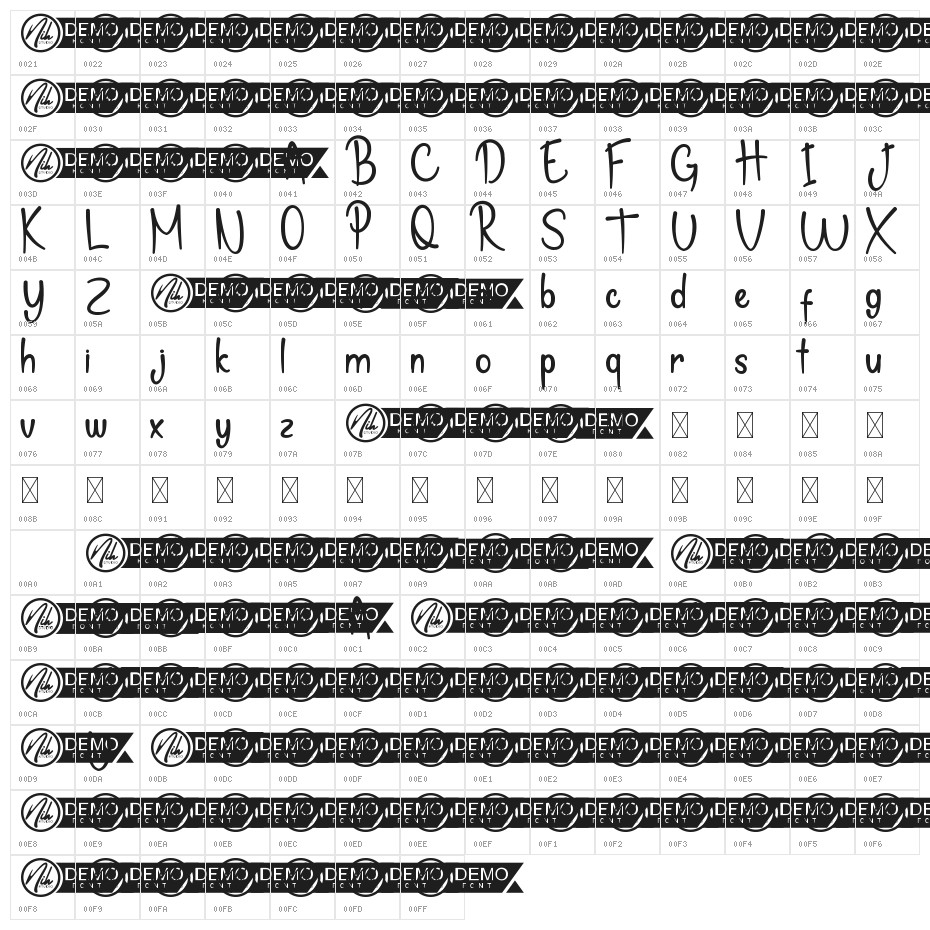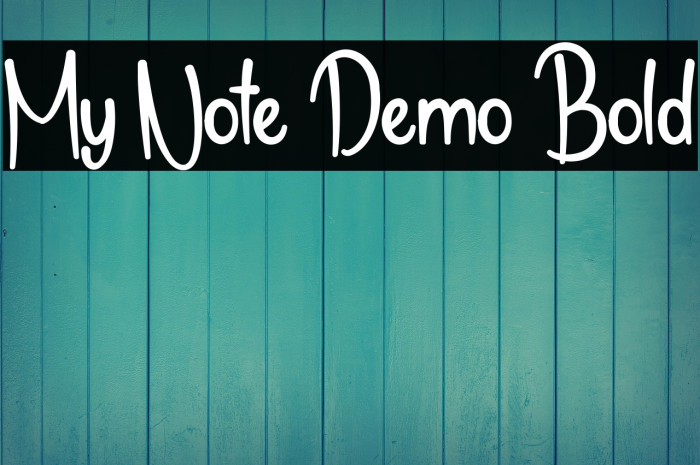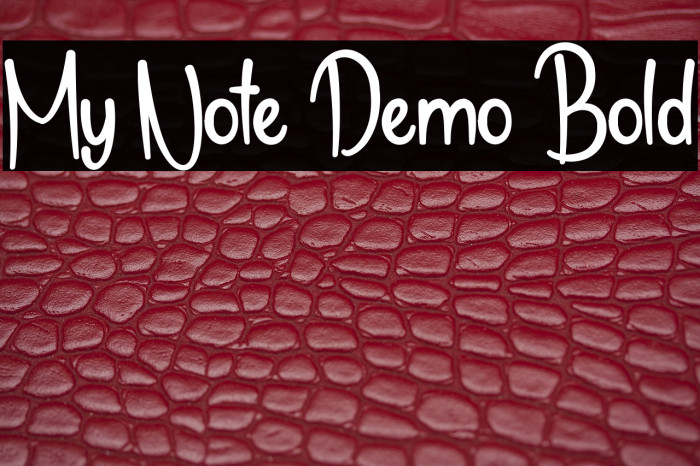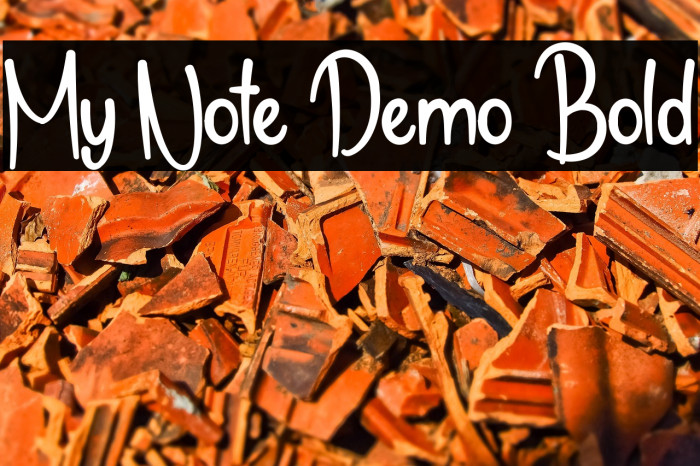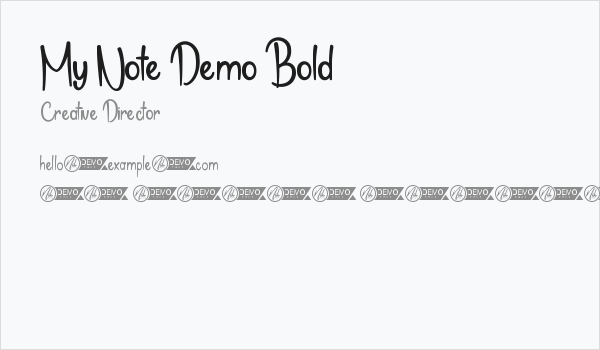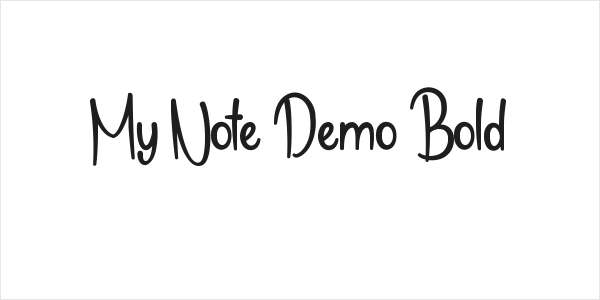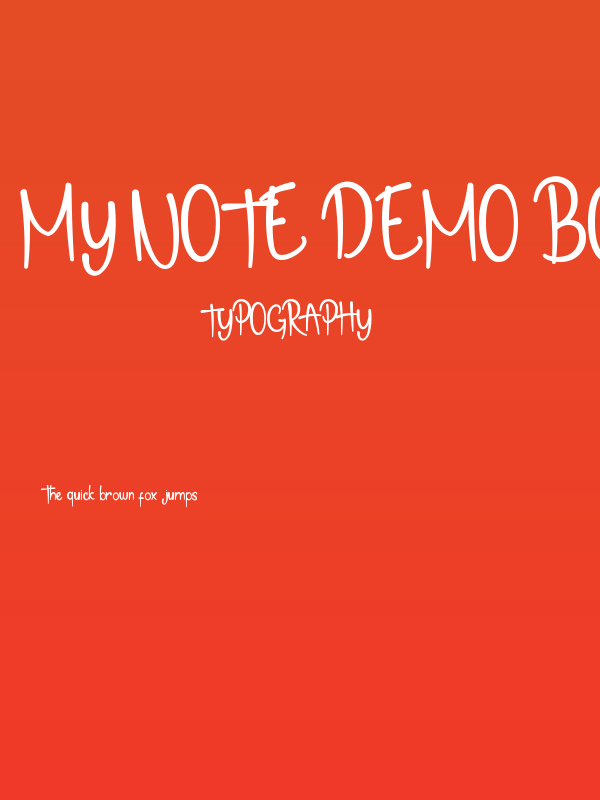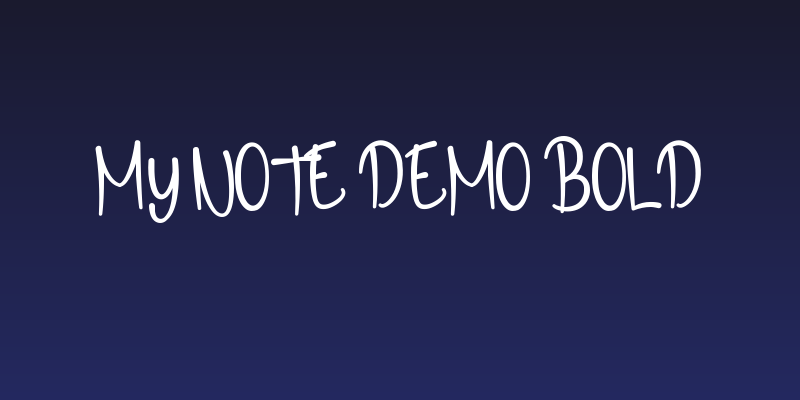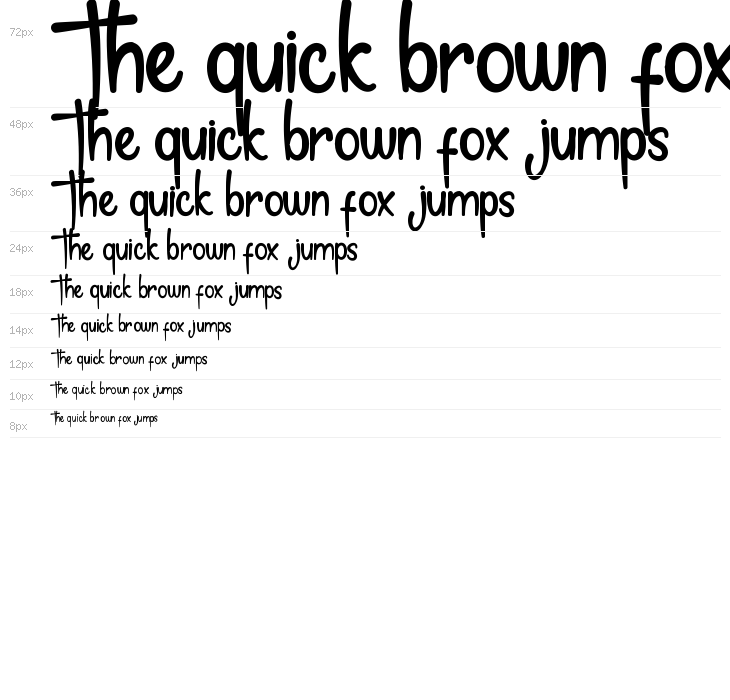
My Note Demo Bold Font
| Stile generale | Casual, Playful |
| Caso d'uso | Headlines, Logos, Informal Text |
| Progetti proposti | Ideal for greeting cards, children's books, playful branding, and social media graphics. |